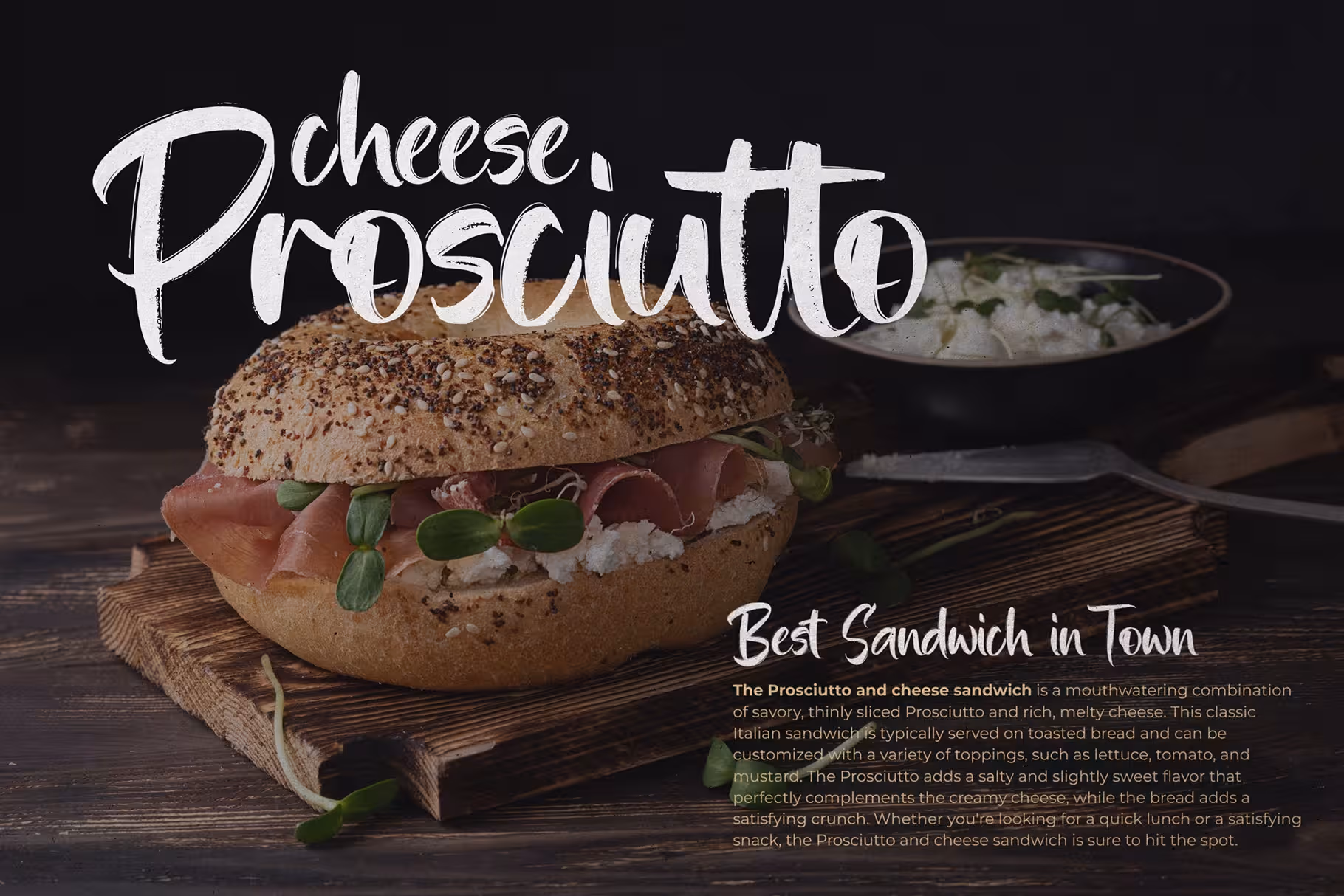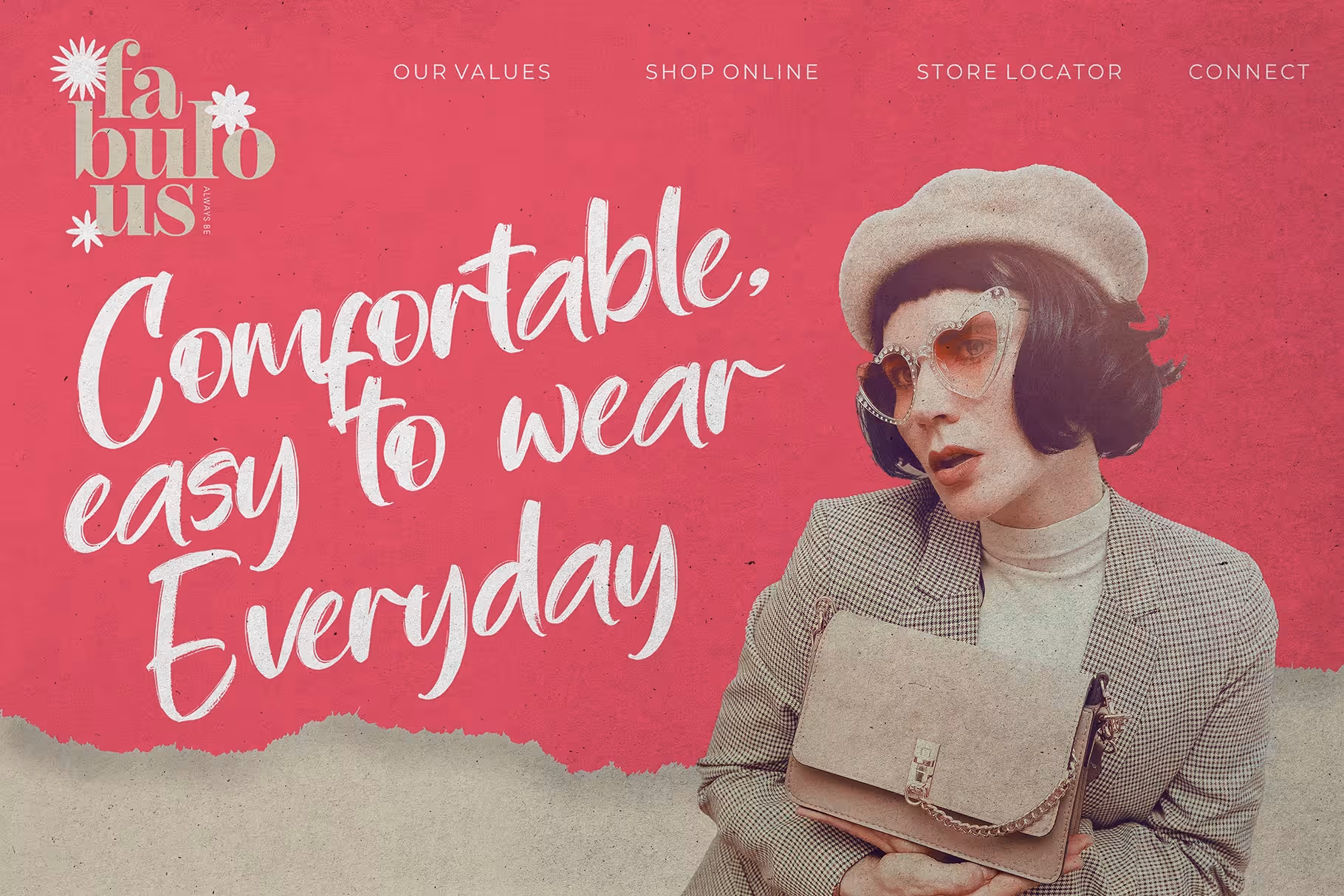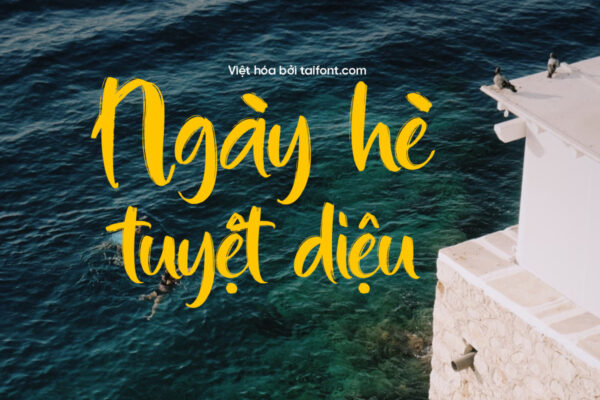
Giới thiệu về Font TF Shutter Breathing Việt hóa
TF Shutter Breathing Việt hóa là một font chữ Brush độc đáo, nổi bật với thiết kế tự do, phóng khoáng và mang phong cách cổ điển. Font này mang đến vẻ ngoài ngẫu hứng, hoài niệm và đầy cá tính, gợi cảm giác về những nét cọ được phẩy một cách tự do, đầy năng lượng. Đây là lựa chọn lý tưởng để tạo điểm nhấn thị giác mạnh mẽ và gây chú ý ngay lập tức, đặc biệt trong các thiết kế liên quan đến ẩm thực và thời trang cổ điển.
Với đặc điểm là nét brush to, đậm, dứt khoát và tính thẩm mỹ cao, Shutter Breathing là lựa chọn hoàn hảo cho các thiết kế muốn truyền tải sự mạnh mẽ, hoài niệm và sự độc đáo, đặc biệt là trong các lĩnh vực:
- Thiết kế ẩm thực: Hoàn hảo để sử dụng trên menu, bao bì sản phẩm, poster quảng bá món ăn, hoặc các ấn phẩm truyền thông của nhà hàng, quán ăn, quán cà phê. Font này giúp món ăn trở nên hấp dẫn hơn, tạo cảm giác ngon miệng và thu hút sự chú ý của thực khách.
- Thiết kế thời trang cổ điển: Lý tưởng cho thương hiệu thời trang, phụ kiện, hoặc các ấn phẩm truyền thông liên quan đến văn hóa, giải trí. Font này giúp tạo dấu ấn cá nhân, sự phá cách và độc đáo cho thương hiệu.
- Thiết kế bao bì sản phẩm: Phù hợp để sử dụng trên nhãn mác, bao bì của các sản phẩm có phong cách mạnh mẽ, năng động, đặc biệt là các sản phẩm liên quan đến đồ uống năng lượng, thực phẩm bổ sung, hoặc các sản phẩm mang tính đột phá và hướng tới giới trẻ.
- In ấn: Đảm bảo khả năng đọc tốt ngay cả ở kích thước lớn, và tạo hiệu ứng thị giác mạnh mẽ khi in trên các chất liệu khác nhau như bảng hiệu, backdrop sự kiện hoặc các ấn phẩm quảng cáo.
Với TF Shutter Breathing Việt hóa, bạn có thể dễ dàng thổi hồn mạnh mẽ, sự độc đáo và cá tính vào các thiết kế, tạo ra những sản phẩm không chỉ đẹp mắt mà còn cực kỳ ấn tượng và có khả năng thu hút sự chú ý tối đa
Font Việt hóa TF Shutter Breathing